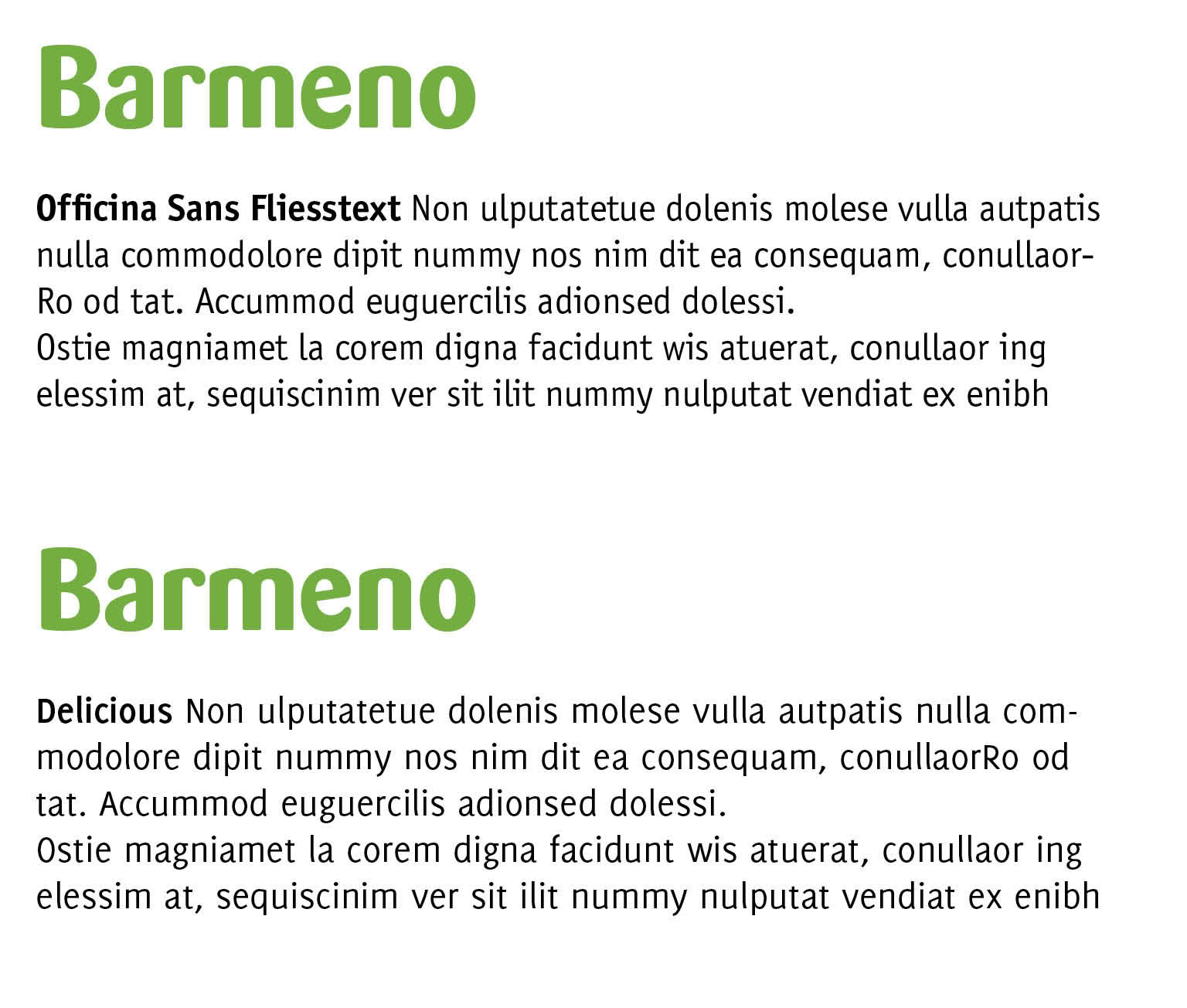
Fliesstextschrift zur Barmeno? Mit Vorschlägen ...
für eine Zeitschrift suche ich eine passende Fliesstextschrift zur Barmeno, also einer dynamischen Serifenlosen. Die Fliesstextschrift sollte möglichst platzsparend sein und mindestens einen kursiven und einen fetten Schnitt dabei haben. Ich dachte schon an die Stone Serif - was meint ihr? Gibt es auch eine passende Serifenlose?
ich könnte mir vorstellen:
platzsparend ist sie und mehr als genug schnitte hat sie auch. ist halt nicht serifenlos.
Hallo Thierry,
danke für den Tipp. Die Weidemann ist mir aber in der Bleiwüste etwas zu konservativ.
Probiere gerade was ganz anderes, was meinst du/ihr hierzu:
solche schriften mit starken, eigenem charakter sind eigentlich schwer mit anderen charakter-typen zu mischen, bzw. mach ich das persönlch eigentlich ungern. ich würde auf etwas ganz neutrales setzen, vielleicht nicht gerade helvetica aber die myriad könnte zum beispiel passen. auch mal anschauen: meta, futura ...
Serifenlos ... die Dax?
war auch mein erster gedanke, gerade wenn man sich die ziemlich daxischen n und m ansieht (obwohl die barmeno natürlich viel älter ist als die dax).
die daxline vielleicht noch am ehesten – obwohl: wenn’s zu ähnlich (und nicht ident) ist, ist die chance groß, dass es sich beißt. müsste man mal ausprobieren.
ich kann die dax ja auch nimmer sehen, aber ich hab mir gedacht: wenn man schon die barmeno verwendet (die ja echt was ziemlich arges ist), dann ist man gegen die dax sowieso immun. :?
och, naja. ist etwas overused. ich würde nur eine barmeno nicht mit einer dax mischen. dafür finde ich die beiden zu ähnlich. im übrigen, ff sari ist die bessere barmeno ;)
weil es myfonts gerade vorschlägt, ff scala sans könnte auch passen — irgendwie.
Alle gute Vortschläge sind bereits gemacht, deswegen noch eine, für eine Schrift die eher "unterused" ist, die Formata. Gibt's halt normal und condensed. Einer der best lesbaren Grotesk-schriften. Macht ein guten Kontrast.